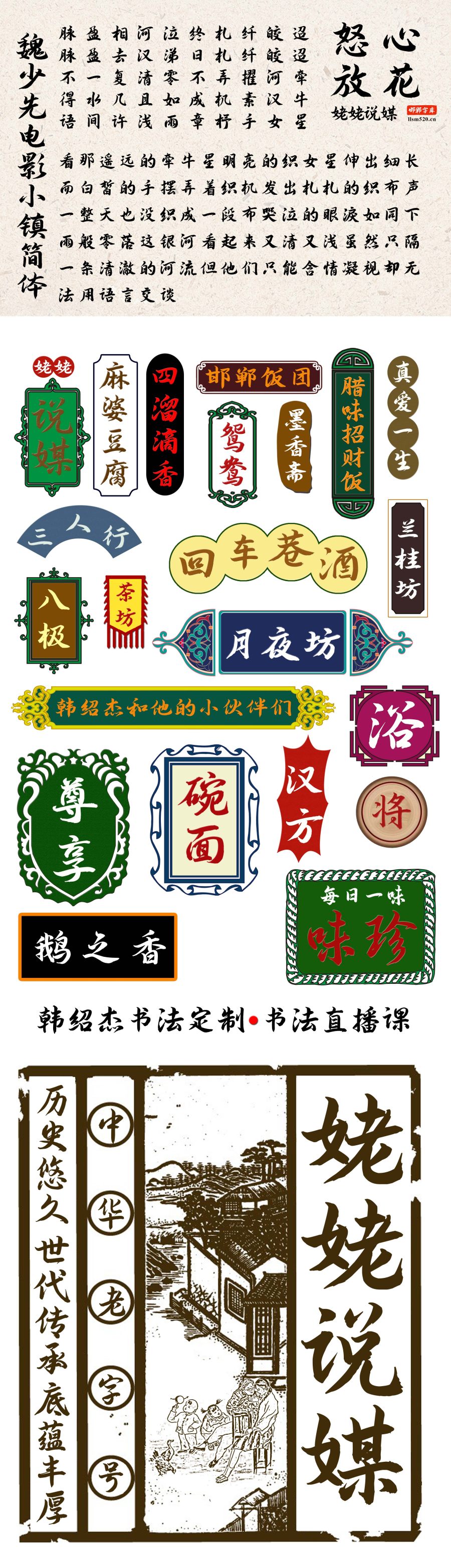
走进《魏少先电影小镇简体》,仿佛走进了一片宽广而雄浑的文化殿堂。这个字体以其开阔雄浑、朗健清逸的特质,令人叹为观止。每一个字母都独立而有力,却又和谐地融入了整体,散发出一种浑然天成的气脉。这种字体贯彻着一种正大、沉毅、豪迈的阳刚精神,以及恢弘独特的美感,让人从始至终都为之倾倒。
《魏少先电影小镇简体》的字体紧密而有力,它展现出一种高雅不俗的气象。这个字体仿佛散发出一种雍容的气息,让人不禁联想到古代王朝的宫廷画卷。在这种字体中,我们可以感受到一种大家风范,一种自信而庄重的态度。
这个字体的设计不仅仅是一种文字的表现,更是一种文化的传承。它将魏少先电影小镇的精神与美感完美地融合在一起,让人们在使用它的过程中,仿佛能够感受到电影的魅力和文化的魔力。